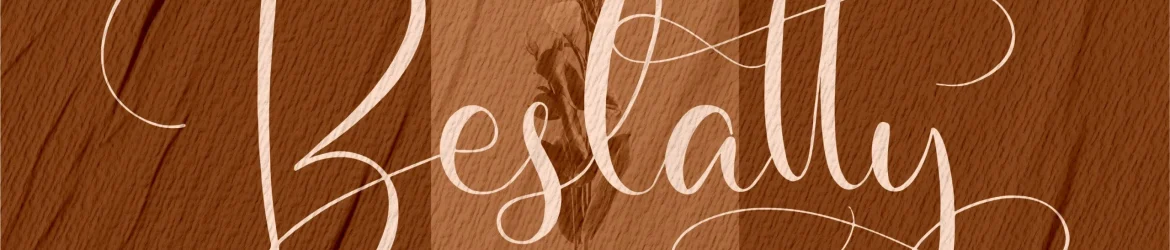
Beslatty Font – Download Grátis
A Beslatty Font é uma elegante tipografia de escrita romântica criada pela Perspectype Studio, perfeita para qualquer projeto onde se deseja dar um toque de delicadeza e elegância à sua ideia. Este script font foi projetado especialmente para incorporar elementos de estilo antigo em designs modernos, tornando-o uma escolha ideal para diversas aplicações. Seja você que está trabalhando em logotipos, criação de marcas, design de produto ou embalagens, Beslatty oferece o elemento necessário para dar um toque pessoal e sofisticado a suas criações. Com seu charme romântico e versatilidade inigualável, Beslatty se adapta perfeitamente a uma variedade de projetos que exigem uma escrita elegante, tornando-o uma fonte indispensável para designers e criativos do Brasil e mundo inteiro.